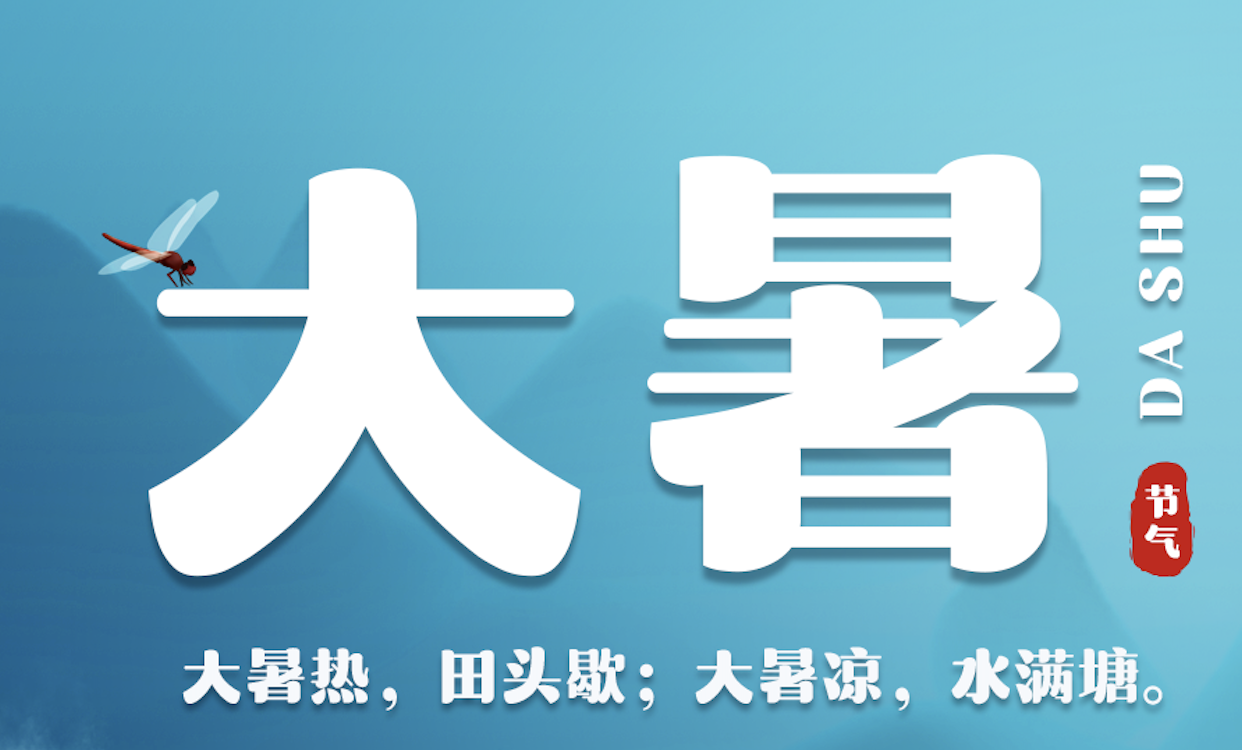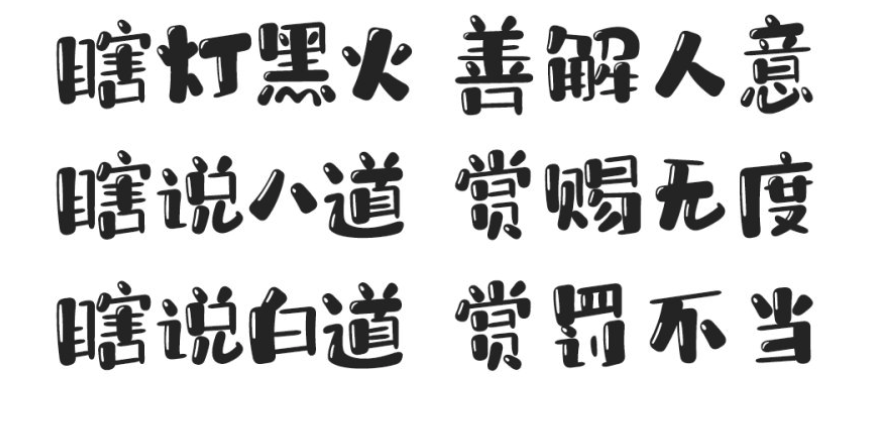
在设计领域中,字体的选择和应用是非常重要的,因为它们能够影响设计作品的视觉效果和风格。随着科技的发展和进步,字体的种类也日趋丰富多彩。
无衬线字体和衬线字体是目前最常用的两种字体类型。无衬线字体(如 Helvetica、Arial)通常被用于现代和科技感较强的设计,而衬线字体(如 Times New Roman、Georgia)则更适用于传统和正式的设计风格。
除此之外,还有一些非传统字体,例如手写字体、创意字体和草书字体等,这些字体能够为设计带来更多趣味和创意元素。
此外,为了满足多语言和多文化的需求,一些支持多语言的字体也开始得到越来越多的应用,这些字体能够满足全球化设计的需要。
在选择字体时,设计师需要综合考虑字体的风格、可读性、适用性和多样性等因素。合理的字体选择和应用能够提高设计作品的质量和美感。
因此,作为设计师,需要对字体有一个深入的了解和应用,以满足不同的设计需求和目标。
总之,字体的多样性和应用是设计中不可或缺的一部分,掌握好字体的选择和应用能够为设计作品带来更多的创意和美感。